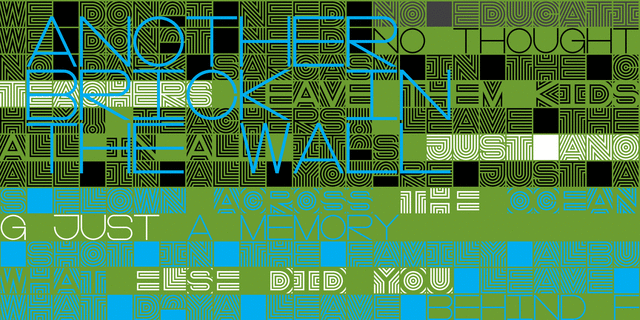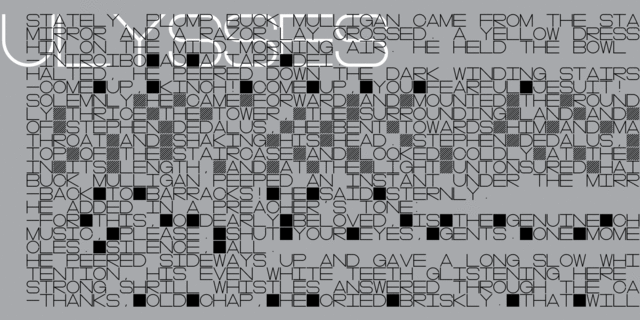
Акцидентная многослойная гарнитура в стиле оп-арт с поддержкой латиницы, кириллицы и греческого. DR Lineart получил награду The Best Of Ukrainian Design in Typestyle and typography 2016. Шрифт разработал Дмитрий Растворцев в 2016-2017 году.
Функции начертания DR Lineart SkeletonПрименение в макете:
Ассоциации c начертанием DR Lineart SkeletonКачества и характер:
тонкий, проволочный, оригинальный, качественный, современный, городской, прозрачный, точный, ровный, ритмичный, экспериментальный, странный, электронный, автоматический, машинный, стальной, компьютерный, острый, резкий, четкий, жесткий, колючий, квадратный, архитектурный, чертежный, инженерный, урбанистичный, техногенный, матричный, индустриальный
Особенности семейства DR LineartХит десятилетия:
Хит 1930-х Хит 1960-х Хит 1970-х Хит 1980-х |